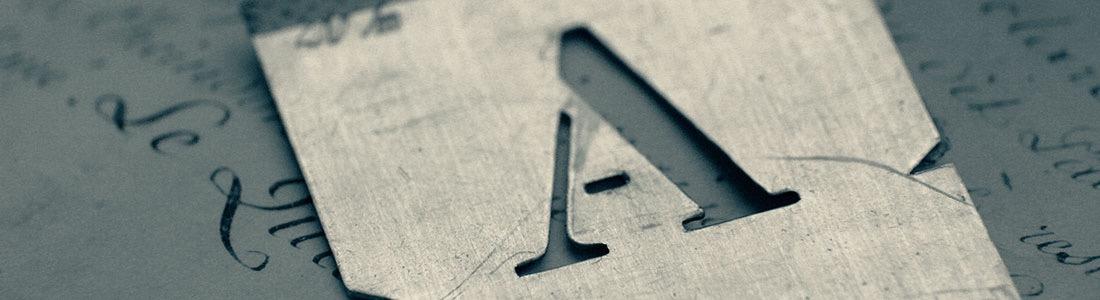
Schablonenschriften (Beispiele) verzichten typischerweise auf geschlossene Binnenformen (Punzen). Im Ergebnis lassen sich mit diesen Schriften oft physische Schablonen zum Zeichnen, Sprühen etc. erstellen. Schriften bzw. Schnitte dieser Art tragen oft die englische Bezeichnung »Stencil« im Namen.
Der typische Stil dieser Schablonenschriften wird aber bei digitalen Schriften auch teilweise als rein stilistisches Merkmal eingesetzt und die Erstellung von Schablonen ist dann nicht immer zwingend möglich.